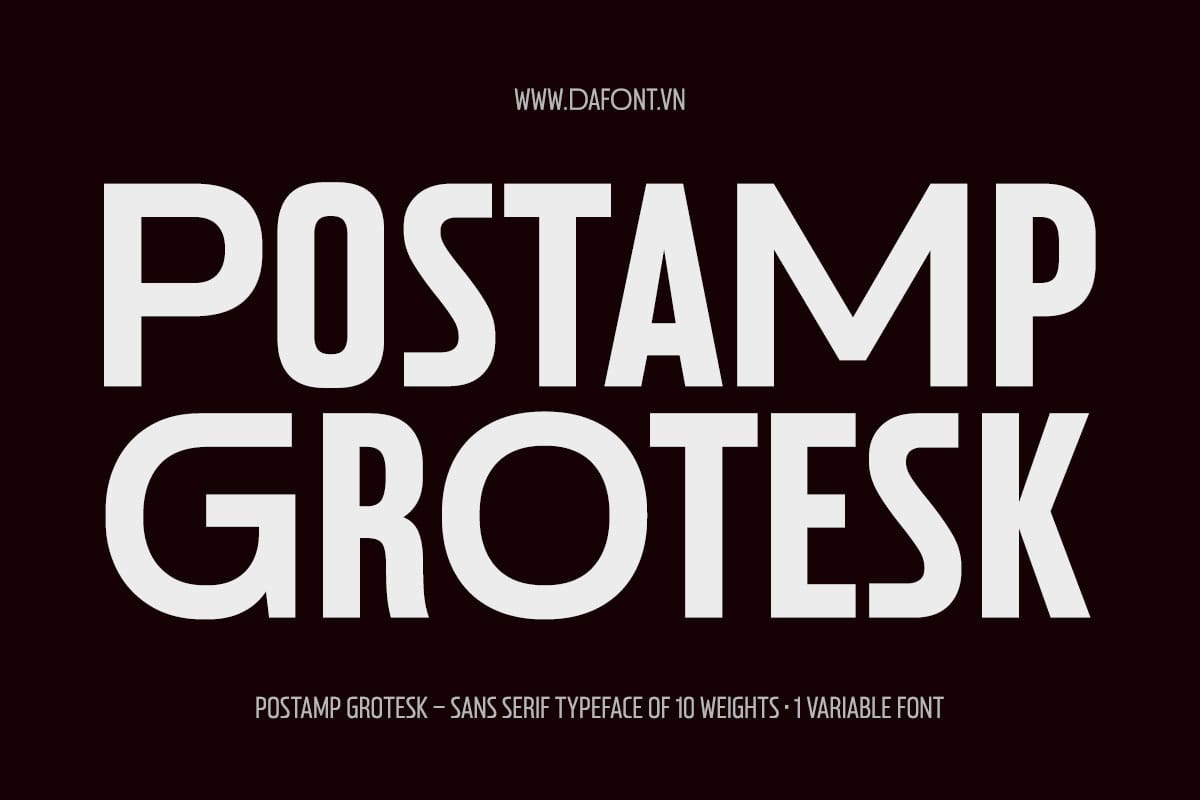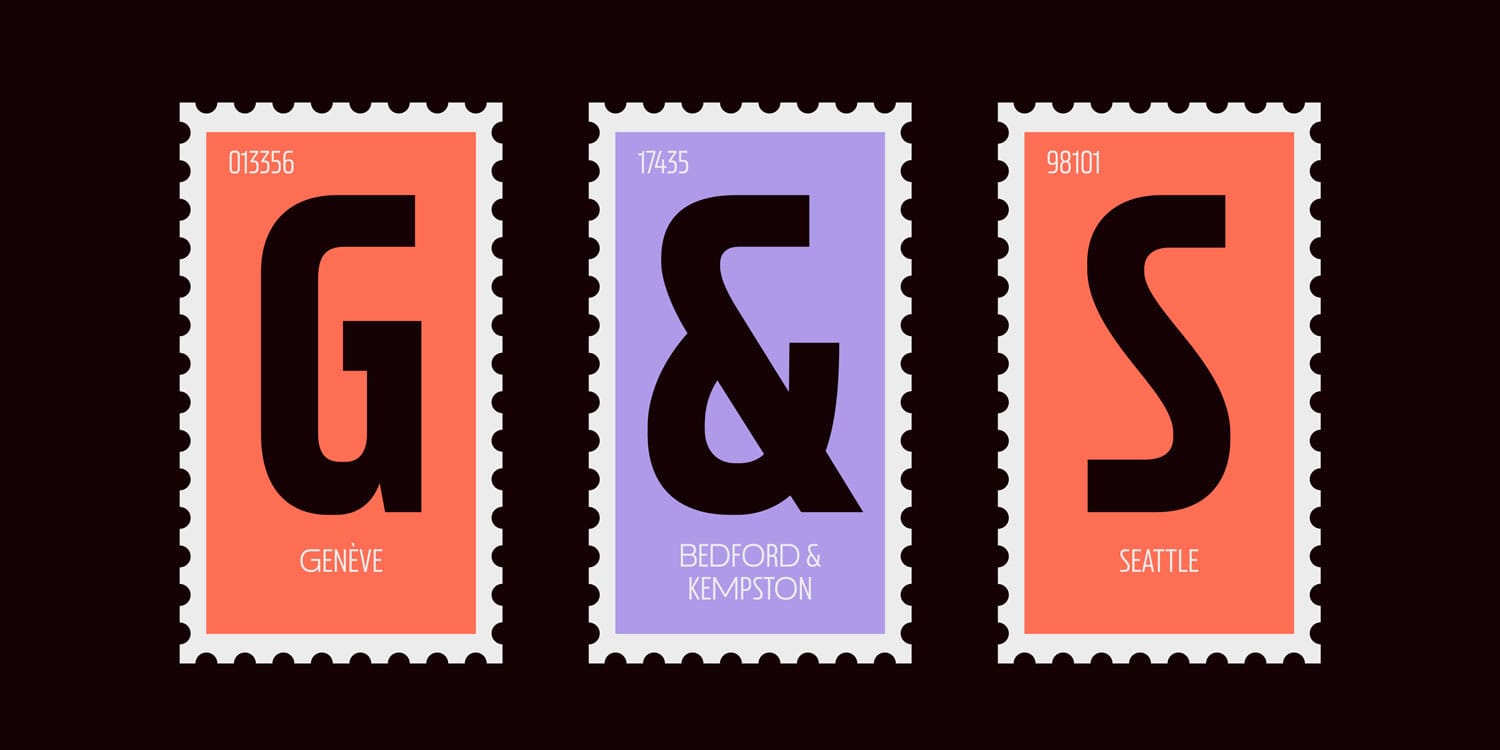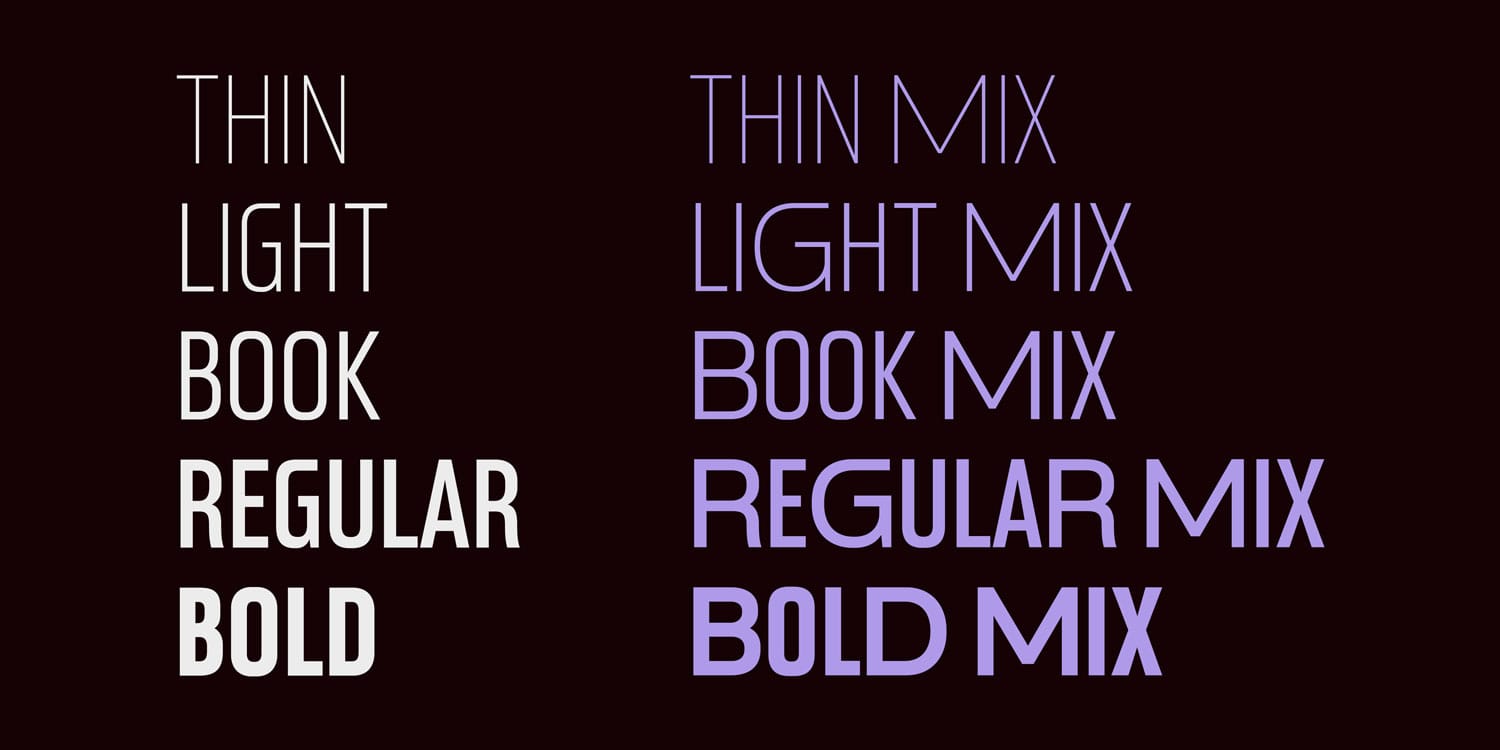
Postamp Grotesk Font Family
Postamp Grotesk là một typeface sans serif hiện đại dạng condensed, kết hợp giữa truyền thống Grotesk và Geometric với tinh thần vintage tinh tế. Lấy cảm hứng từ typography Mỹ vào cuối thế kỷ 19 và đầu thế kỷ 20 – đặc biệt là kiểu chữ xuất hiện trên những con tem bưu chính lịch sử của Hoa Kỳ – Postamp Grotesk tái diễn giải các dáng chữ condensed cổ điển dưới một góc nhìn đương đại.
Điểm khởi đầu của thiết kế là một con tem bưu chính Hoa Kỳ có hình Tổng thống James Buchanan. Các dáng chữ đặc trưng trên con tem đã mở ra hành trình nghiên cứu sâu hơn về typography trên tem và các mẫu chữ Mỹ thời kỳ đầu, để rồi phát triển thành một họ font display linh hoạt. Với đầu nét mở (open terminals), tỷ lệ gọn, và hình học được cân chỉnh kỹ lưỡng, Postamp Grotesk gợi lại nét thanh lịch của thập niên 1920 – 1930 nhưng vẫn mang cảm giác hiện đại rõ rệt.
Điểm nổi bật Postamp Grotesk Font
Condensed thường gắn với mục tiêu “tiết kiệm chiều ngang”, nhưng nếu lạm dụng có thể gây cảm giác khô và đều tăm tắp. Postamp Grotesk xử lý vấn đề này bằng cách đưa vào các ký tự có độ rộng mở rộng có chọn lọc (ví dụ các ký tự B, C, D, G, M, O, P, R…), giúp dòng chữ condensed vẫn có nhịp điệu, có điểm rơi thị giác và dễ tạo phong cách riêng cho tiêu đề.
Với 5 weight, 2 trục biến thiên (weight và width), các tính năng OpenType, và hỗ trợ Latin + Cyrillic, Postamp Grotesk thích ứng mượt mà với nhiều bối cảnh sáng tạo. Hãy nâng tầm thiết kế của bạn với một typeface tự tin, tập trung và khác biệt rõ rệt.
Gợi ý cặp font hoàn hảo kết hợp với Postamp Grotesk
Chọn đúng cặp font có thể nâng tầm thiết kế, tạo cân bằng, tương phản và hòa hợp thị giác. Postamp Grotesk với cấu trúc hình học condensed và dáng chữ thoáng, kết hợp rất tốt với những typeface tạo được nhịp điệu và độ tương phản. Một số gợi ý:
• Nexa Serif cho bố cục editorial và thiết kế tạp chí
• Matt cho UI và phần text dài
• Mont, Chopin cho hệ thống branding có cấu trúc
Những kết hợp này bổ trợ vẻ hiện đại của Postamp Grotesk, đồng thời tăng khả năng đọc và phân cấp thông tin.